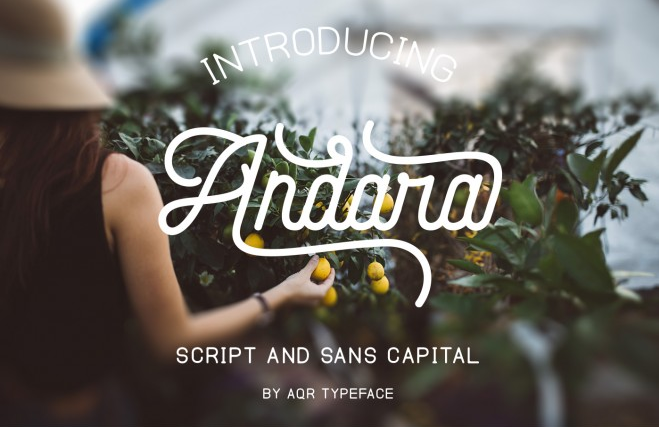
Andara Script Font – Download Grátis
A fonte “Andara Script Font” é uma combinação única de script manual e tipo leve, que proporciona uma experiência visual agradável para diversos projetos. Este conjunto de scripts e tipos leves oferece um excelente equilíbrio perfeito para qualquer produto ou negócio. A fonte se destaca especialmente para projetos vintage ou clássicos, como gráficos de fotografia ou criação de marcas, destacando-se por sua facilidade e elegância. Dayatz2009 é o criador desta fonte livre de uso pessoal, disponível na plataforma PayHip. Para um uso comercial, os usuários podem acessar diretamente o link fornecido para obter as permissões necessárias. É uma opção incrivelmente versátil e prática, oferecendo aos designers uma ferramenta poderosa para expressarem seus projetos de design de forma única e profissional.
Designer: dayatz2009